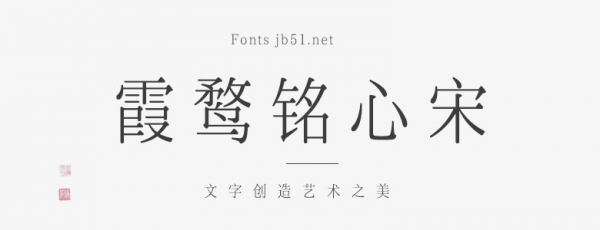
霞鶩銘心宋在こころ明朝體的基礎(chǔ)上修改制作,將新致宋字面橫向壓縮 85%,并增加圓角,更加清瘦、圓潤。(注:銘心宋所收字符相比于新致宋會有所欠缺,敬請留意。)
霞鶩銘心宋目前包含 GB/T 2312-1980 一級字、《通用規(guī)范漢字表》一級字、《現(xiàn)代漢語常用字表》3500 字。